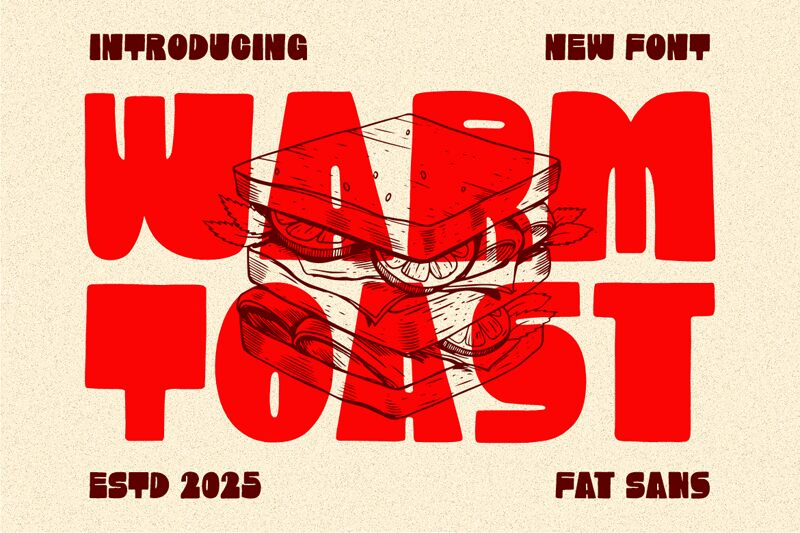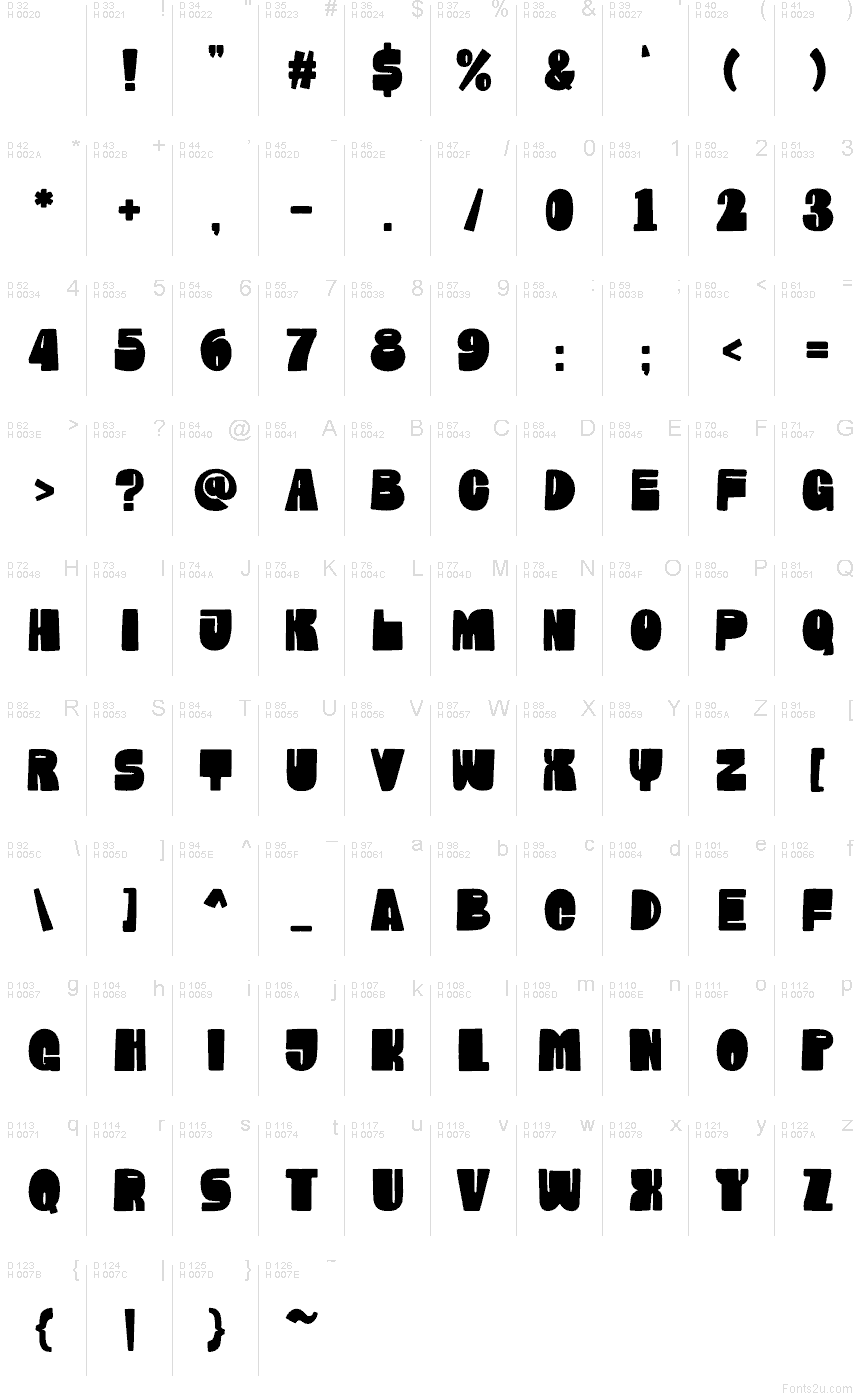
Warm Toast, de Shanaf Studio, es una tipografía display gratuita de estilo groovy con una silueta densa y recortada a mano. Sus letras anchas se expanden en formas suaves e irregulares, con aberturas estrechas y uniones ceñidas. La variación de anchos aporta dinamismo a la línea en lugar de un aspecto mecánico.
Los diseñadores que trabajen para marcas desenfadadas de alimentación, música o dirigidas al público juvenil pueden utilizarla en envases de aperitivos, carteles de festivales y merchandising. Su volumen rotundo, similar a una tostada, encaja a la perfección en la rotulación de cafeterías y en publicaciones infantiles, donde las formas irregulares pueden integrarse en escenas ilustradas.